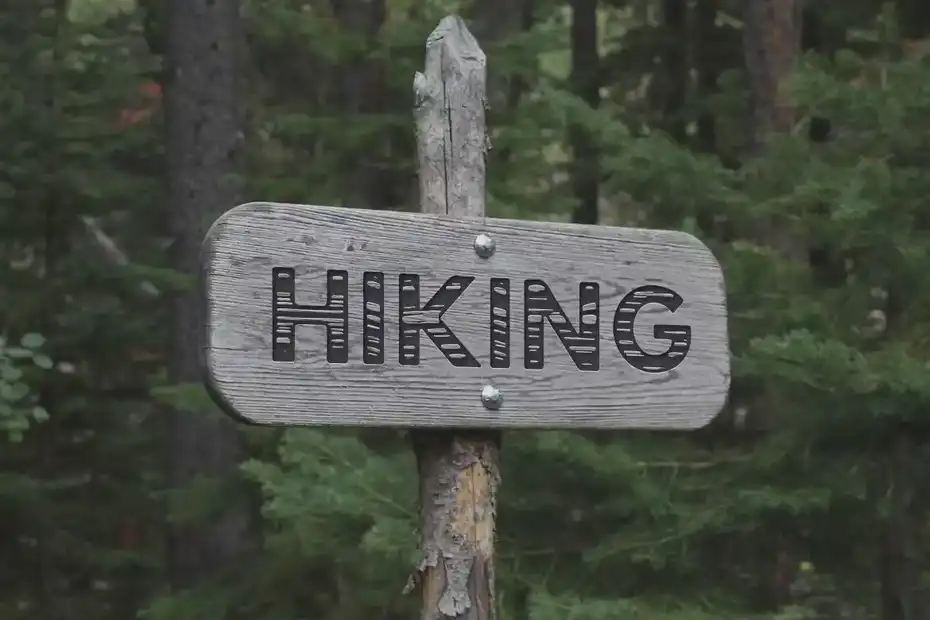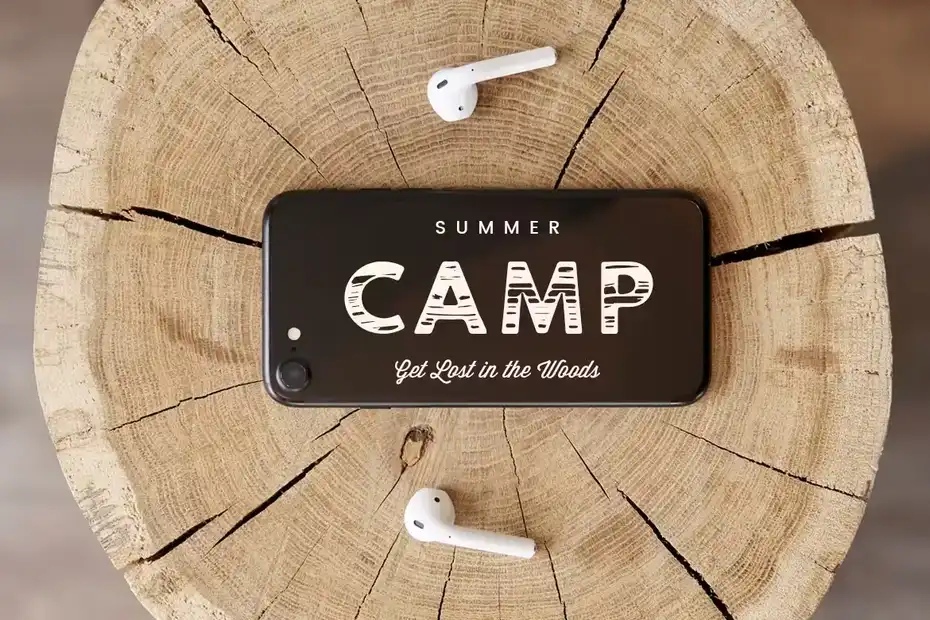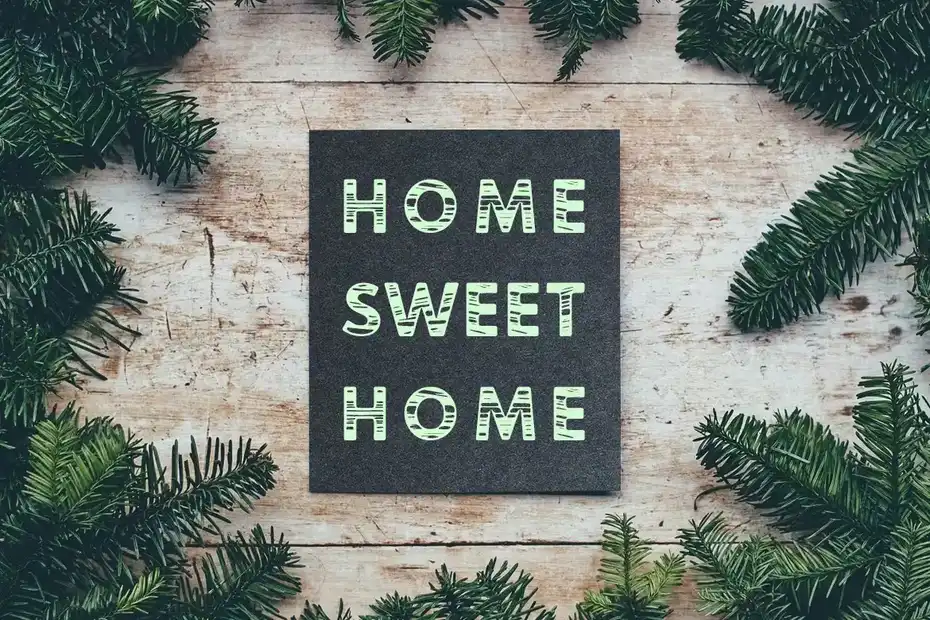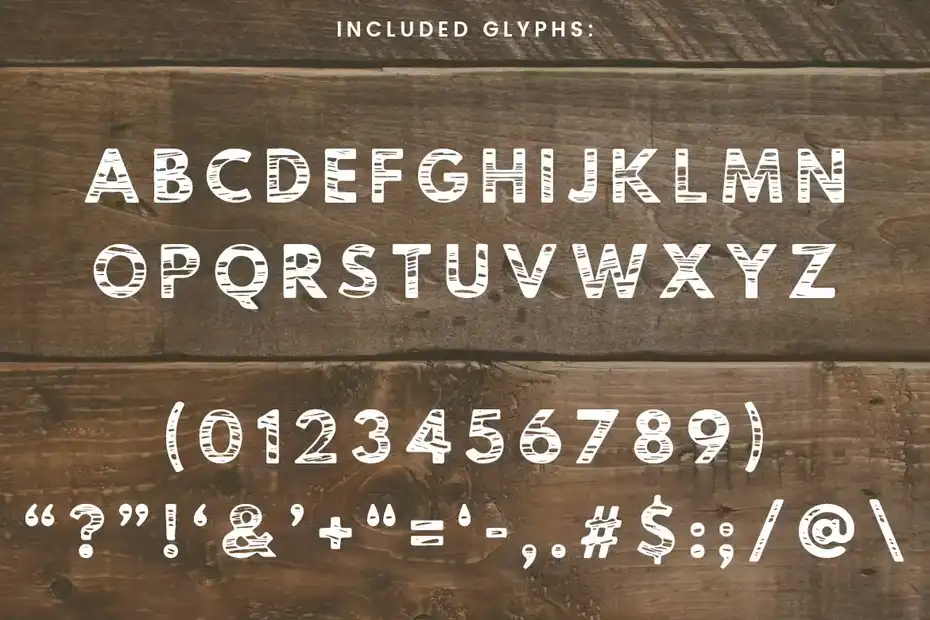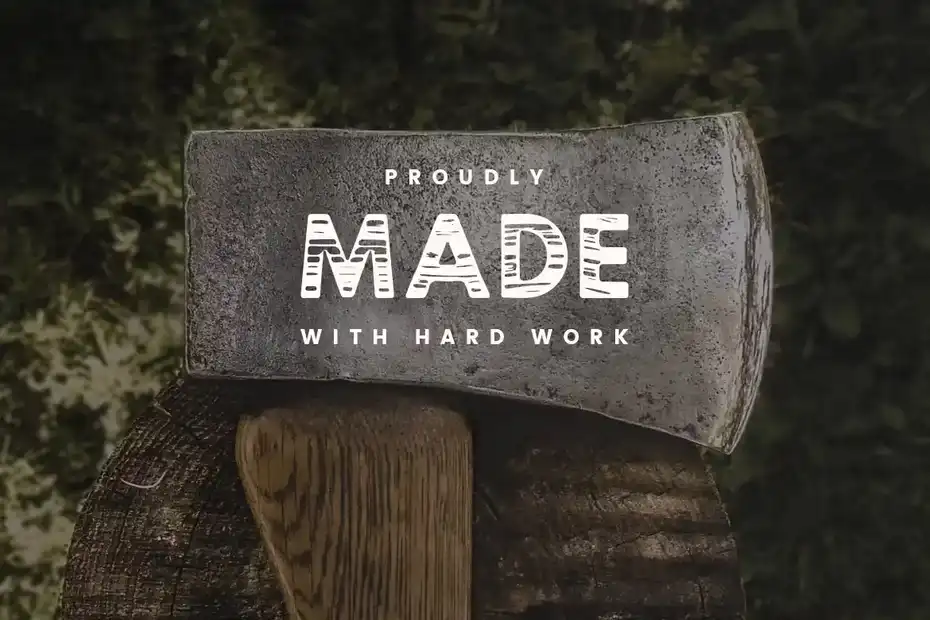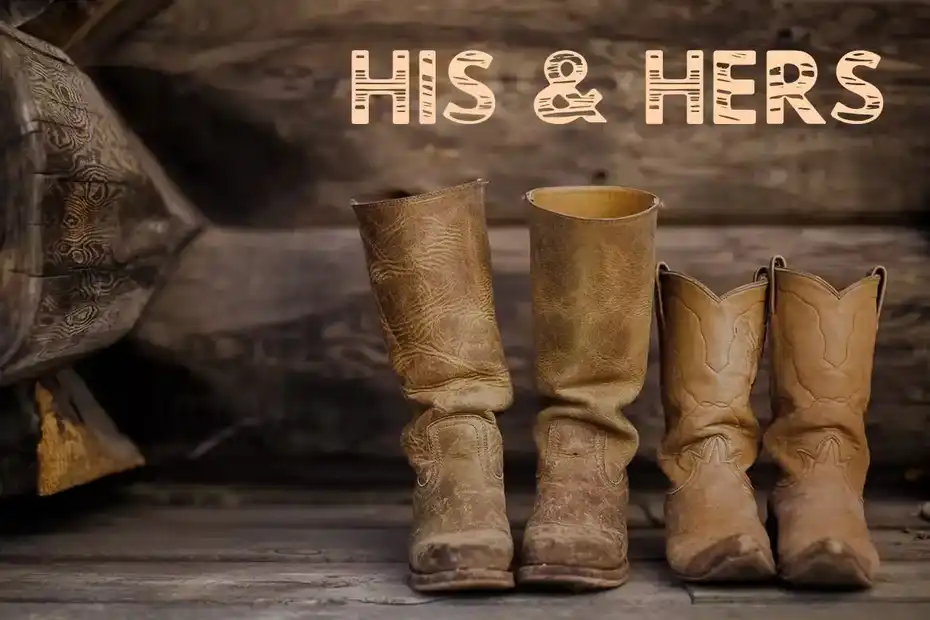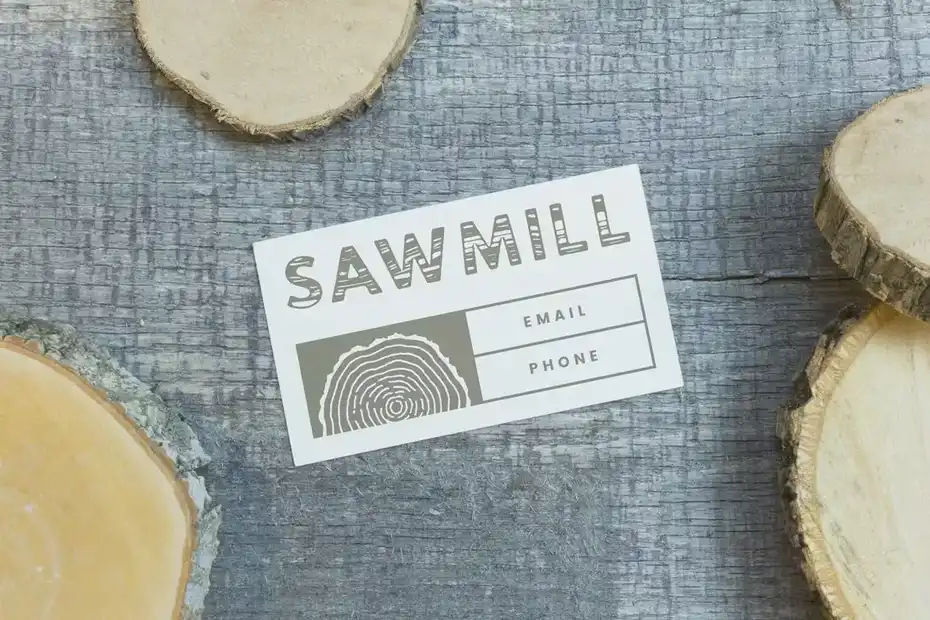
فونت انگلیسی گرافیکی Timber Hitch Font : این مجموعه شامل یک فونت انگلیسی به سبک Sans-Serif با بافت چوبی روستیک است که برای پوستر، پوشاک، کارت عروسی روستیک، لوگو و غیره مناسب میباشد.
• عنوان مجموعه: Timber Hitch Font + Bonus Nature Elements
• سبک: Sans-Serif